Les typographies gothiques dans le design moderne : quand tradition rime avec tendance
Au carrefour de l’ombre et de la lumière, la typographie gothique s’infiltre à nouveau dans le design contemporain avec une intensité fascinante. Ce retour, loin d’être un simple clin d’œil au passé, prend place sur la scène graphique comme un héritage à la fois profond et surprenant, où tradition et modernité s’entrelacent pour former un dialogue visuel inédit. La délicatesse de caractères tels que Garamond ou Baskerville, la force austère du Blackletter, et même les harmonies plus singulières du Fraktur se redéfinissent dans des univers où le crépuscule n’est plus seulement esthétique mais aussi conceptuel.
Dans cet article, nous explorerons comment les typographies gothiques imprègnent le design d’aujourd’hui, sur les traces de leur lange médiéval tout en révolutionnant leur fonction et leur résonance. Des polices classiques aux choix audacieux, chaque élément traduit une volonté de renouer avec une histoire à la fois dense et mystérieuse, mais aussi avec une expressivité vibrante qui irrigue les productions graphiques les plus actuelles. Ce mouvement dépasse la nostalgie pour devenir une tendance active, un souffle qui traverse affiches, interfaces et identités visuelles.
Une exploration des racines des typographies gothiques dans l’histoire du design
L’influence des typographies gothiques puise sa source dans le Moyen Âge européen, notamment dans la période dite gothique qui a marqué les arts et l’architecture. La typographie dite Blackletter, aux lignes anguleuses et complexes, est sans doute la plus emblématique de cette époque. Apparue aux alentours du XIIe siècle, elle reflète l’austérité et le mysticisme qui imprégnaient les manuscrits médiévaux. On la retrouve dans le Fraktur allemand, un style qui, malgré sa connotation parfois polémique à travers l’histoire, continue de fasciner par son tracé ornementé et son épaisseur graphique.
Les polices comme Garamond, Baskerville, ou Caslon, bien que plus proches des styles romans ou classiques, portent la trace de cette histoire gothique par leur lente évolution vers plus de lisibilité, tout en gardant un certain charme traditionnel. Elles incarnent un dialogue entre la rigueur et la grâce qui traverse les siècles. Dans le domaine du design moderne, cette influence historique se traduit par une manière de jouer avec la texture, de chercher, dans la forme des lettres, une identité visuelle riche de sens et de suggestions.
Cette tradition ne se limite pas à un simple héritage décoratif : elle est une matière vivante pour les graphistes qui, parfois, s’inspirent du contraste entre les lettres romaines à la Futura ou Helvetica et les courbes dramatiques d’un Didot ou Bodoni. Ce contraste révèle une tension fertile entre héritage et innovation que beaucoup de projets contemporains embrassent, spécialement dans des univers liés à la culture alternative ou à la scénographie graphique gothique.
- Blackletter : une écriture médiévale principalement utilisée dans les documents religieux et officiels.
- Fraktur : variétés allemandes de Blackletter, reconnu pour sa densité et son style ciselé.
- Garamond : typographie élégante, dérivée de la Renaissance, appréciée pour sa lisibilité et sa finesse.
- Baskerville : plus moderne, avec une forte influence classique, utilisée pour des impressions luxueuses.
- Caslon et Didot : symboles de sophistication avec leurs traits contrastés et leur clarté.
| Typographie | Origine historique | Caractéristiques graphiques | Usage contemporain |
|---|---|---|---|
| Blackletter | Moyen Âge | Traits anguleux, densité, ornementation complexe | Identité forte, affiches, designs alternatifs |
| Fraktur | Allemagne médiévale | Formes découpées, traits ciselés | Projets historiques et culturels |
| Garamond | Renaissance française | Finesse, élégance, grande lisibilité | Édition, luxe, mode |
| Baskerville | XVIIIe siècle, Angleterre | Contrastes forts, formes classiques | Imprimés haut de gamme, branding |
| Caslon | Début XVIIIe siècle | Style robuste, lisibilité pour la presse | Journaux, affiches |
| Didot | Fin XVIIIe siècle | Traits fins et contrastés, élégance | Mode, publicité, luxe |
| Bodoni | Fin XVIIIe siècle, Italie | Contrastes extrêmes, géométrie rigoureuse | Design éditorial, marques fortes |
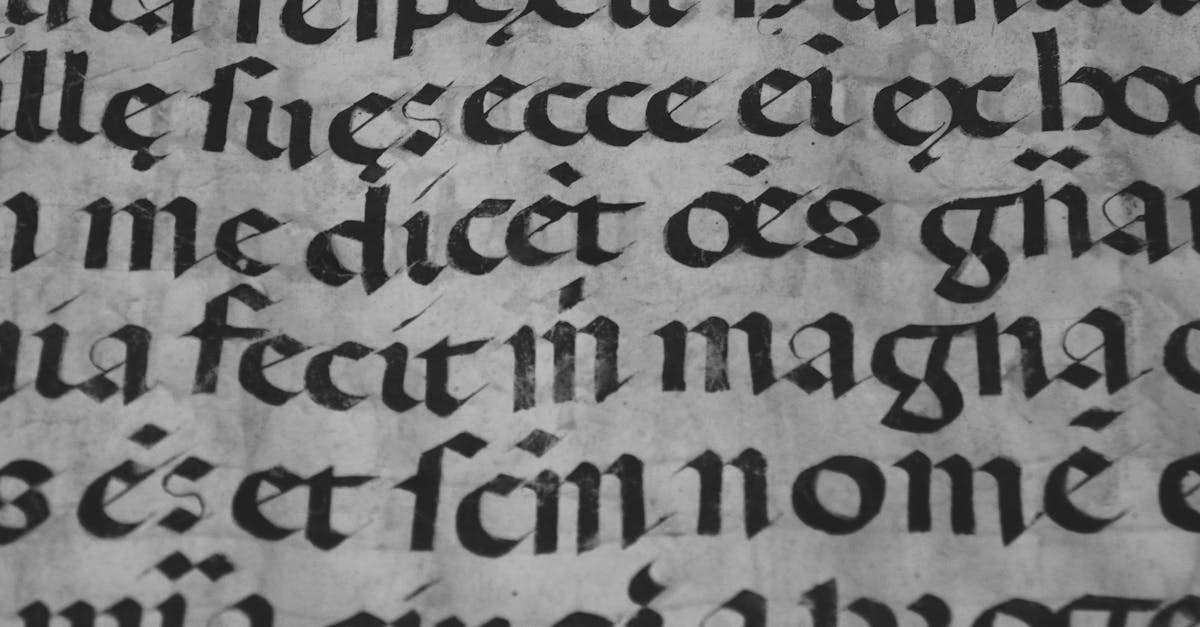
La renaissance des typographies gothiques dans la conception graphique actuelle
À mesure que le design avance dans cette nouvelle décennie, les typographies d’esprit gothique connaissent un renouveau significatif. Cette renaissance n’est pas qu’un phénomène esthétique isolé, elle répond à une soif de sens, d’authenticité et d’une certaine gravité visuelle dans un monde saturé de visuels éphémères. Les designers contemporains entendent ainsi revitaliser les caractères comme Blackletter ou Fraktur dans des contextes qui pouvaient paraître jusqu’ici incompatibles avec leur force historique.
Ce retour s’inscrit aussi dans un courant plus large qui revisite l’histoire des typographies, cherchant dans la profondeur des caractères classiques une manière d’insuffler une nouvelle vie à l’identité visuelle. Ainsi, certaines entreprises acceptent de rompre avec les polices ultra-modernes telles que Futura ou Helvetica au profit de choix plus chargés de symbolique. L’usage de ces polices plus travaillées transmet souvent une gravité et un mystère qui confèrent à l’objet graphique une valeur presque rituelle.
- Q : Quelles sont les tendances actuelles autour de la typographie gothique en 2025 ?
R : L’exploration de typographies hybrides, les effets 3D, et l’usage des outils d’IA pour personnaliser la création typographique sont les grandes tendances qui marquent cette période.
- Q : Peut-on utiliser les typographies gothiques dans le design inclusif ?
R : Oui, en veillant à respecter les critères d’accessibilité, notamment les contrastes de couleurs et la lisibilité, qui sont des exigences grandissantes dans le design moderne.